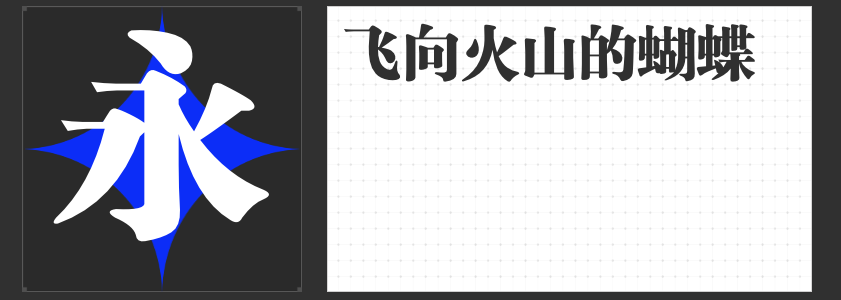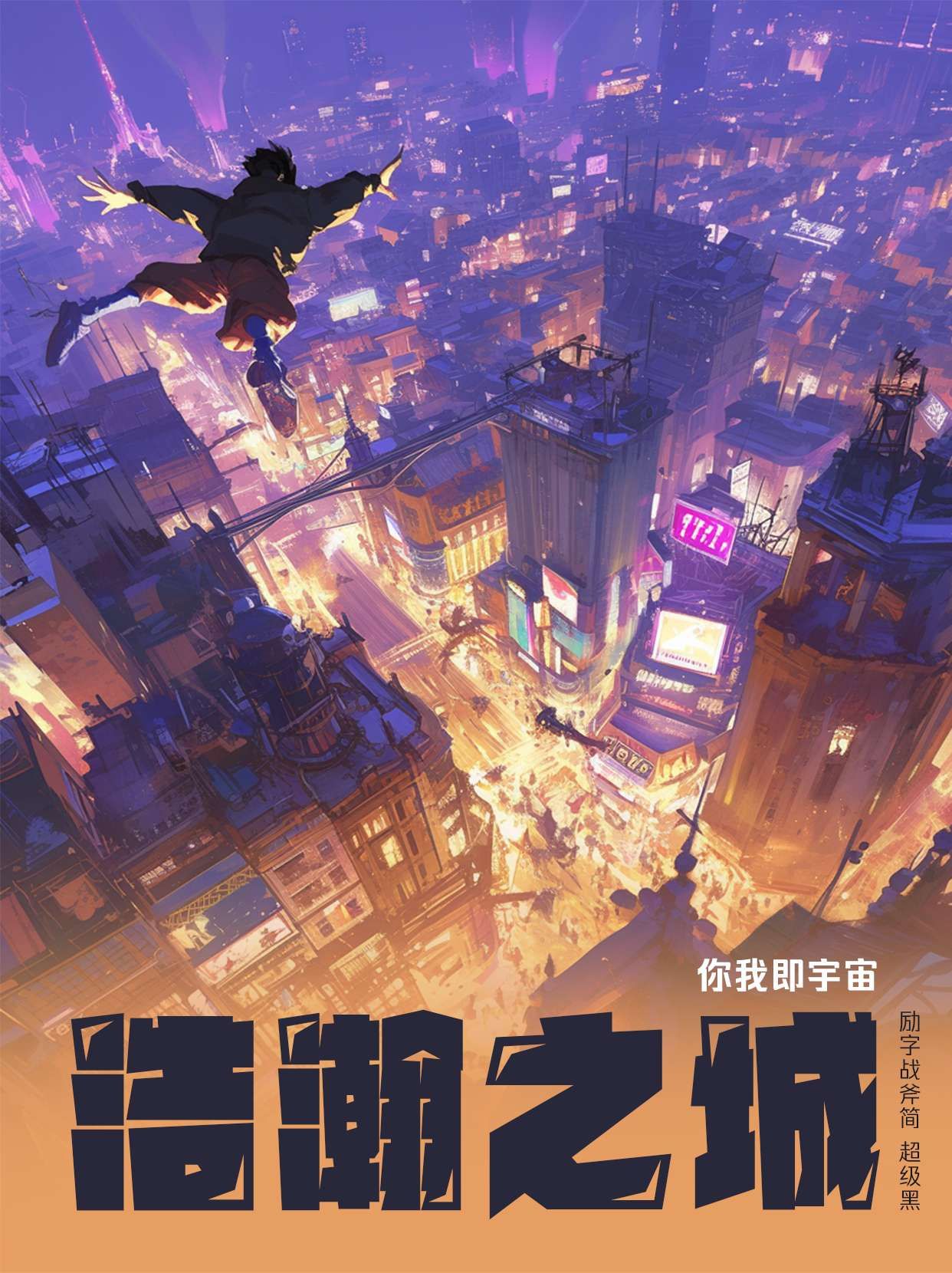
四款匠心标题字体推荐👁为设计注入独特魅力
在设计领域,标题字体是吸引目光、传递信息的关键元素。今天,为大家推荐四款各具特色的标题字体,它们不仅美观独特,更能精准表达设计意图,让作品脱颖而出。
一、励字新粗宋简
励字新粗宋简,一款打破传统结体方式的宋体变奏。它保留了宋体字横细竖粗的基本特征,却在笔画末端巧妙加入装饰部分,点、撇、捺、钩等笔画尖端处理精致,赋予字体更多灵动与变化。字型扁方,既显稳重又不失时尚感,非常适合用于需要传统韵味又不失现代感的设计标题。
二、励字造战斧黑
励字造战斧黑,一款充满现代创意的黑体佳作。字型厚重而富有张力,笔画粗细不均,横竖呈梯形分布,展现出强烈的视觉冲击力。撇、捺、点中融入更多梯形元素,左上和右下的对角高光设计,更是让这款字体风格鲜明,大标题字的特征一览无余。它非常适合科技、时尚或需要强烈现代文艺氛围的设计项目。
三、喵字文案体
喵字文案体,专为文案行业量身打造。它融合了传统书法的韵律与现代设计的简洁,每一笔都透露出知性之美。此字体强调阅读的流畅性和视觉的舒适度,无论是广告创意、品牌故事还是社交媒体内容,都能精准捕捉文案的精髓,让文字充满温度和力量。喵字文案体,是文案工作者的得力助手,让每一句话都闪耀独特魅力。
四、励字山中精灵简
励字山中精灵简,一款充满童趣与活力的标题字体。笔画饱满圆润,无尖锐边角,留白空间恰到好处,转折处可爱灵动。这款字体辨识度极高,风格统一且应用性强,可以拉伸使用而不失美感。线条富有节奏与灵气,布白均匀,为设计带来一股清新可爱的氛围,非常适合用于儿童、动漫或需要轻松愉悦感的设计标题。
这四款标题字体,各具千秋,无论是传统与创新的融合、现代文艺的硬朗表达、知性之美的细腻呈现,还是圆润可爱的视觉盛宴,都能为你的设计增添独特魅力,让标题成为作品的点睛之笔。